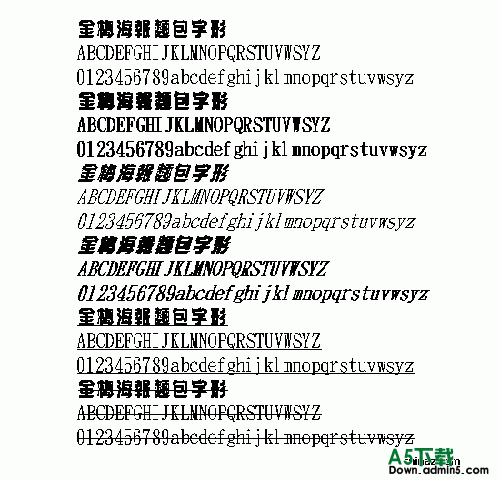
金梅海報(bào)面包字形(繁)是一個(gè)專(zhuān)門(mén)用來(lái)設(shè)計(jì)海報(bào)廣告的繁體字形,字體圓潤(rùn)飽滿(mǎn),需要的朋友快來(lái)綠色資源網(wǎng)里下載試試吧!
金梅海報(bào)面包字形是文鼎字體庫(kù)中一種字體,常用于美工設(shè)計(jì)方面,喜歡的朋友不要錯(cuò)過(guò)。